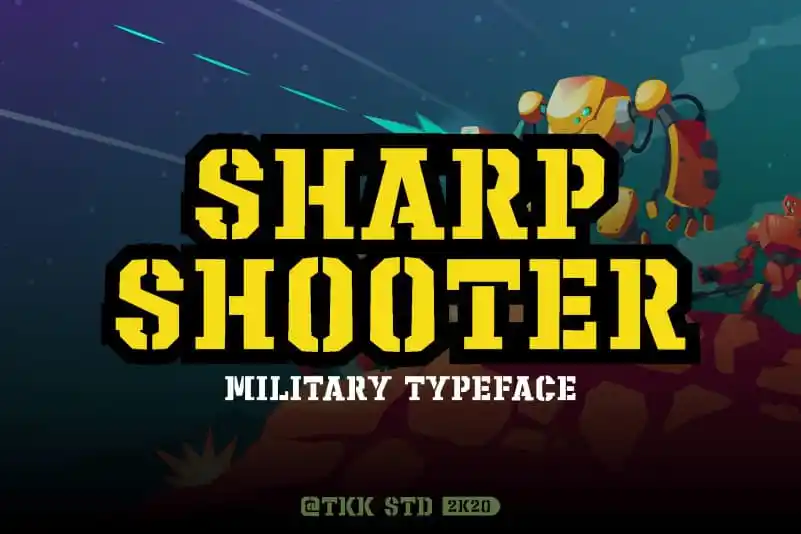
Descubra “Sharpshooter Display Font”, uma elegante, forte y desafiadora fuente de iluminado ideal para criar elementos visuais impactantes e modernos. Especialmente indicada para ambientes que valorizam a simplicidade e o poder visual, essa fuente foi criada pela Tokokoo Studio para destacar seu estilo militar. Com sua forma clara e limpa, “Sharpshooter Display Font” oferece um contraste entre elementos sólidos e desenhados ao ar livre, criando uma combinação elegante que promove a simplicidade e o foco. Ideal tanto para títulos notáveis quanto para subtítulos poderosos em qualquer projeto visual, essa fuente é perfeita para quem busca um estilo audaz no design de fontes. Sua facilidade de uso e forte contraste garantem uma experiência de usuário intuitiva, tornando-a uma escolha irresistível para aqueles que desejam estabelecer o tom certo em seus projetos visuais.